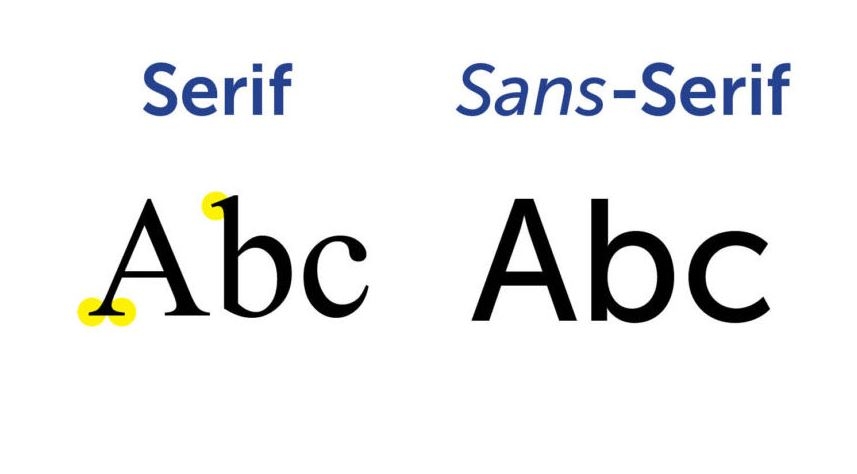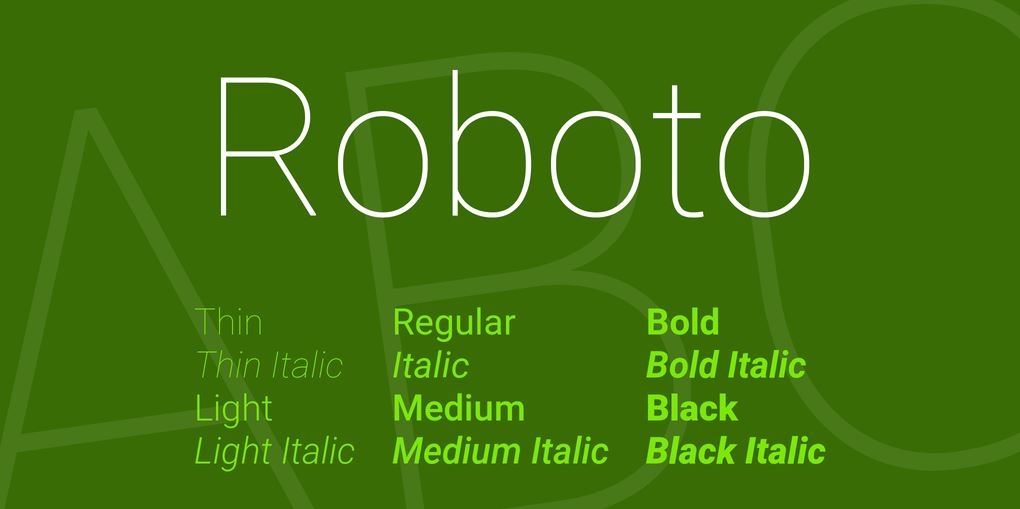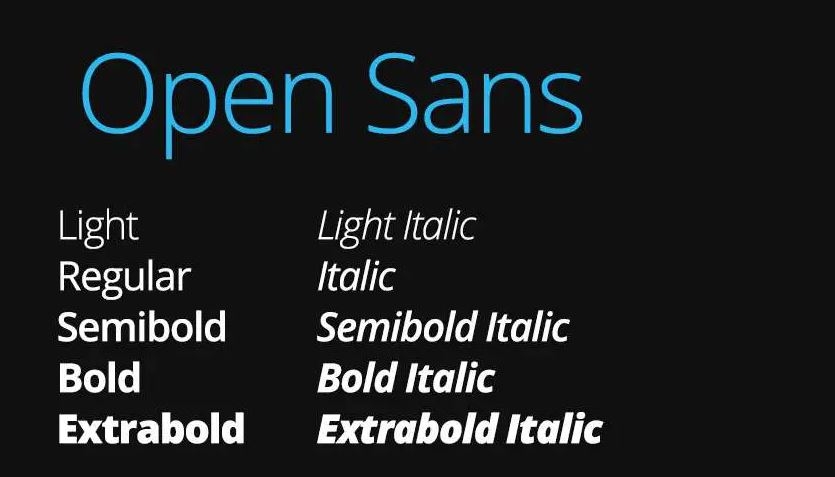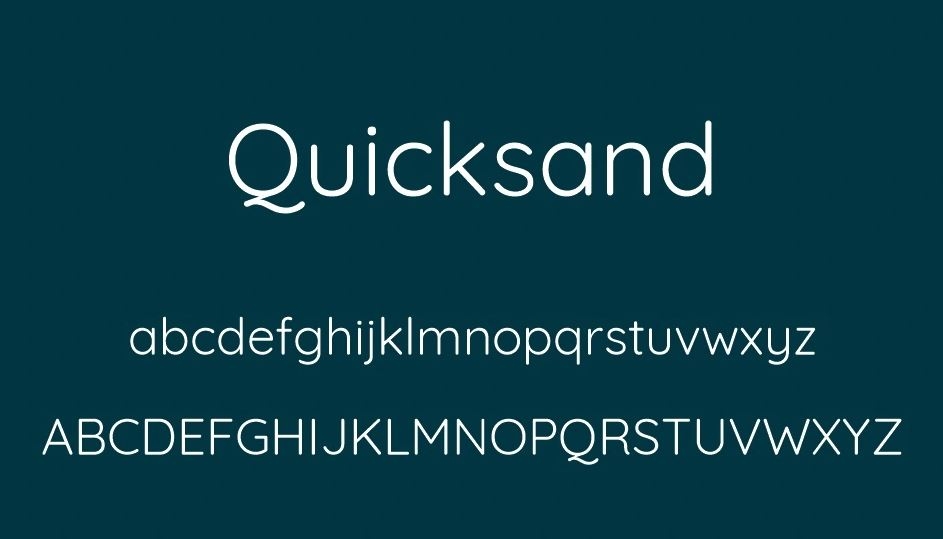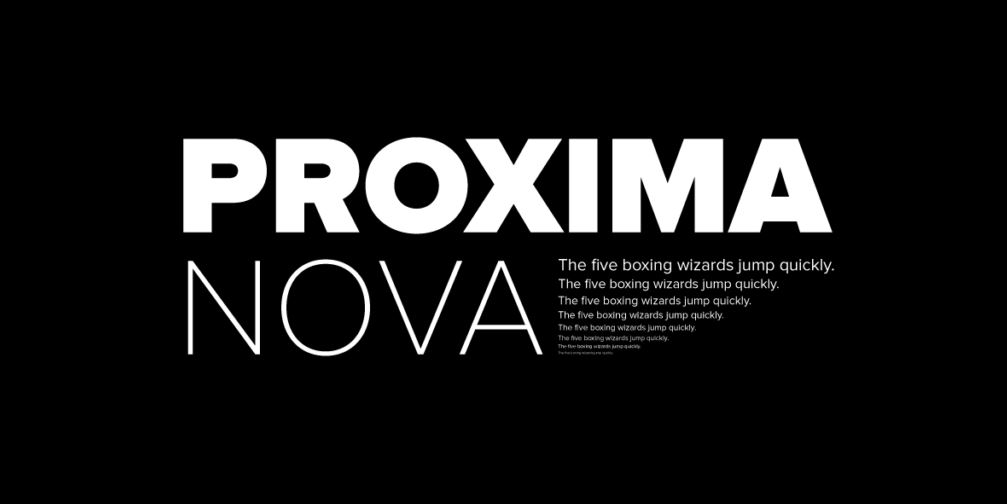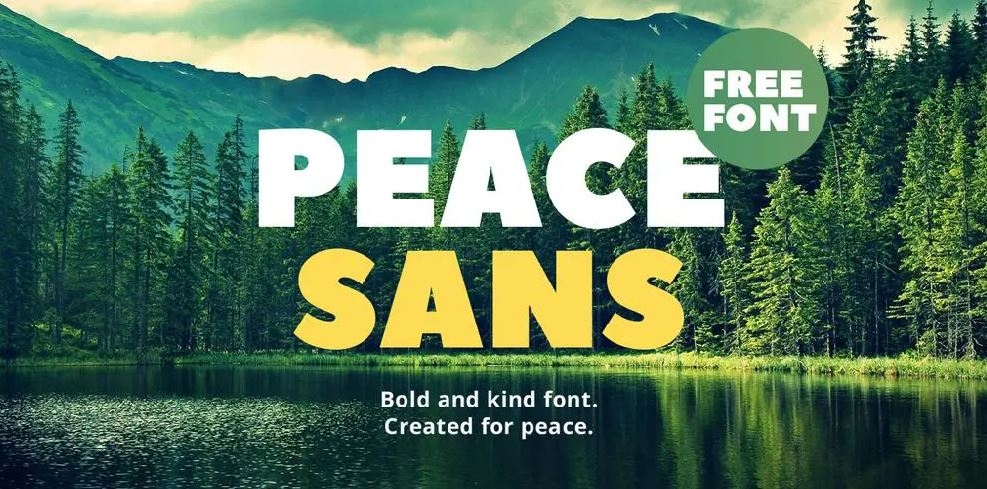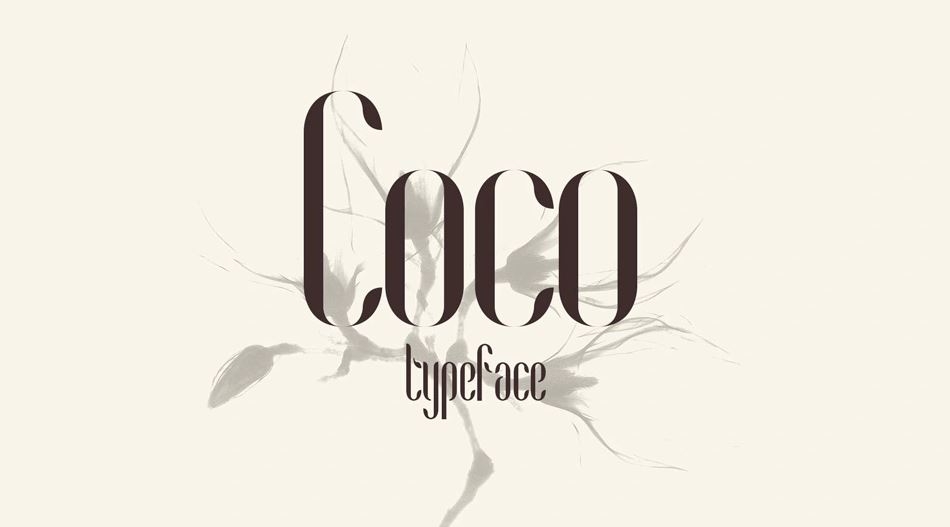
Tổng hợp 10 font chữ không chân được Việt hóa đẹp dùng trong thiết kế ấn phẩm
Trong thiết kế đồ họa, font chữ là một phần không thể thiếu để tạo nên tổng thể hài hòa, ấn tượng. Một trong những font được sử dụng phổ biến hiện nay là font chữ không chân hay còn gọi Sans Serif. Cùng tìm hiểu về font chữ không chân qua nội dung bài viết này nhé.
Font chữ không chân là gì?
Font chữ không chân (Sans Serif) là một kiểu chữ không có các đường kẻ nhỏ ở cuối các ký tự. Các đường kẻ này được gọi là Serif. Font chữ không chân xuất hiện lần đầu vào thế kỷ 19 và thực sự phổ biến vào thế kỷ 20.
Đối ngược với font chữ có chân Serif, font chữ Sans Serif trông hiện đại, các đường nét khỏe khoắn hơn mang lại sự trẻ trung, sáng tạo hơn. Hơn nữa, font chữ không chân ít gây mỏi mắt, dễ đọc phù hợp trong thiết kế website, slide trình chiếu hay các ấn phẩm online.
Sans Serif có những ưu điểm nổi bật như sau:
- Font chữ không chân có đường nét thanh mảnh, rõ ràng, không có những đường kẻ nhỏ ở dưới nên dễ đọc, không làm rối mắt người nhìn.
- Font chữ mang hơi hướng hiện đại, trẻ trung thích hợp với nhiều mục đích sử dụng khác nhau.
- Sans Serif được sử dụng trong nhiều lĩnh vực khác nhau như thiết kế logo, thiết kế trang web, thiết kế banner, poster, brochure,... thu hút người nhìn.
Tuy nhiên, font chữ Sans Serif cũng có một số nhược điểm là có thể gây khó đọc nếu để kích thước quá nhỏ và không thể hiện được sự sang trọng, cổ điển như font chữ có chân.
Font chữ không chân được ứng dụng linh hoạt trong nhiều lĩnh vực khác nhau, trong đó gồm:
- Thiết kế trang web: Font chữ không chân là lựa chọn hàng đầu của các nhà phát triển website. Bởi font chữ được thiết kế tối giản, rõ ràng, loại bỏ phần chân chữ giúp trải nghiệm người dùng tốt hơn, không gây mỏi mắt khi đọc trên máy tính, điện thoại, máy tính bảng.
- Thiết kế nhận diện thương hiệu: Với phong cách trẻ trung, hiên đại, font chữ không chân được ứng dụng mạnh mẽ trong thiết kế quảng cáo, bộ nhận diện thương hiệu như logo, banner, brochure, bao bì,... để tạo sự chú ý của người nhìn.
Tổng hợp 10 font chữ không chân Việt hóa đẹp
Bạn đang cần tìm font chữ không chân để hoàn thiện ấn phẩm của mình nhưng chưa biết lựa chọn font chữ phù hợp? Đừng lo, dưới đây là các font chữ không chân đã Việt hóa được nhiều người sử dụng để bạn tham khảo.
1. Helvetica Now
Helvetica Now là một trong những font chữ được sử dụng phổ biến nhất trên thế giới. Tuy chỉ mới ra mắt vào năm 2019, nhưng font chữ đã có sức ảnh hưởng lớn đến nhiều lĩnh vực và đang được cải tiến, phát triển để phù hợp với xu hướng người dùng. Với kiểu chữ thanh mảnh, đơn giản nhưng sang trọng, Helvetica Now được ứng dụng nhiều trong thiết kế web, thiết kế nhận diện thương hiệu như logo, banner, poster. Font chữ được tập đoàn Microsoft, Jeep dùng để tạo điểm nhấn thương hiệu.
2. Futura
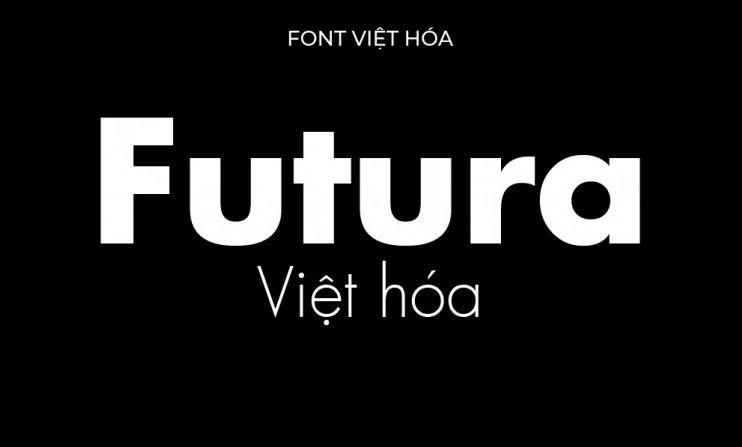
Furuta được thiết kế bởi Paul Renner vào năm 1927. Đây là font chữ không chân cổ điển nhưng đậm phong cách hiện đại với thiết kế thanh thoát, đơn giản. Font được ứng dụng nhiều trong thiết kế logo, thiết kế thương hiệu, thiết kế bao bì, poster,...
3. Arial
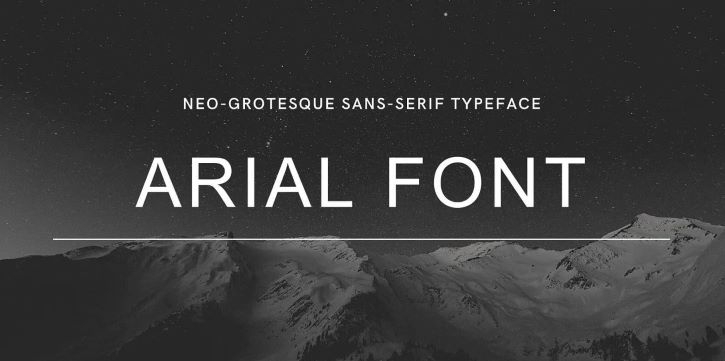
Arial cũng là một trong những font chữ không chân phổ biến, được người dùng đánh giá cao về tính thẩm mỹ và khả năng dễ đọc. Font được thiết kế bởi Robin Nicholas và Patricia Saunders vào năm 1982. Arial thường được sử dụng cho các tiêu đề, văn bản, thiết kế logo, banner,...
4. Calibri
Xuất hiện đầu tiên vào năm 2007, Calibri là font chữ không chân được dựa trên font Arial do Lucas de Groot thiết kế. Calibri thường được sử dụng làm font chữ mặc định cho ứng dụng Microsoft Office như Word, Excel và PowerPoint. Với kiểu dáng hiện đại, đơn giản, font chữ được sử dụng trong thiết kế trang web và các ứng dụng di động.
5. Roboto
Roboto là một font chữ Sans Serif được thiết kế bởi Christian Robertson và phát hành bởi Google. Phông chữ được sử dụng làm font chữ hệ thống cho hệ điều hành Android và các sản phẩm, dịch vụ khác của Google.
Font Roboto có đường nét rõ ràng, tạo cảm giác mạnh mẽ, mang phong cách hiện đại. Tuy nhiên, font chữ cũng có các đường nét mềm mại tạo cảm giác cởi mở, thân thiện. Phông chữ có nhiều phiên bản khác nhau từ Thin đến Black cho người dùng sử dụng đa dạng trong thiết kế ấn phẩm.
6. Open Sans
Open Sans là font chữ không chân miễn phí và được hỗ trợ mã nguồn mở. Phông có kiểu dáng hiện đại và đa dạng biến thể khác nhau như Regular, Italic, Bold và Bold Italic giúp người dùng ứng dụng linh hoạt trong thiết kế. Open Sans thường được áp dụng trong các giao diện website, ứng dụng di động, phần mềm văn phòng mã nguồn mở LibreOffice, tài liệu in ấn và nhiều ứng dụng khác.
7. Quicksand
Quicksand là font Sans Serif hiện đại với các đường cong mềm mại cùng với sự thanh lịch và đều đặn trong từng ký tự. Phông chữ thường được chọn để tạo nên vẻ nhẹ nhàng, thân thiện cho các sản phẩm thiết kế. Quicksand có nhiều biến thể với các kiểu chữ in nghiêng, in đậm giúp tạo hiệu ứng, thu hút người xem trong các ấn phẩm thiết kế. Phông được sử dụng cho nhiều mục đích như thiết kế đồ họa, in ấn, xây dựng website.